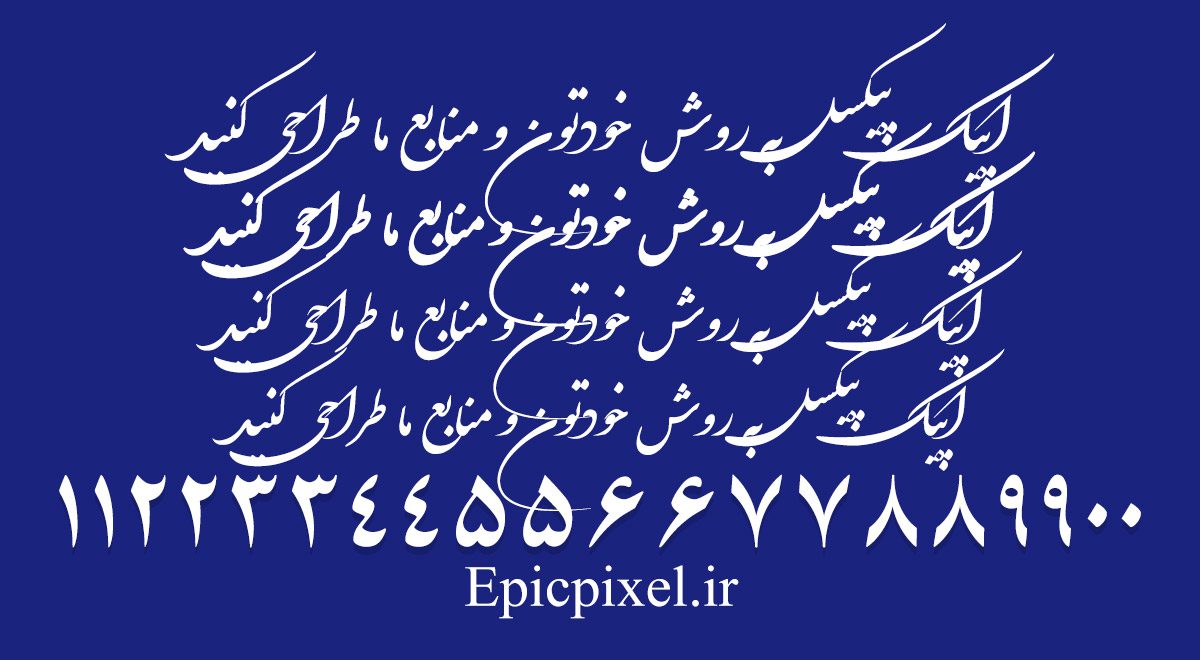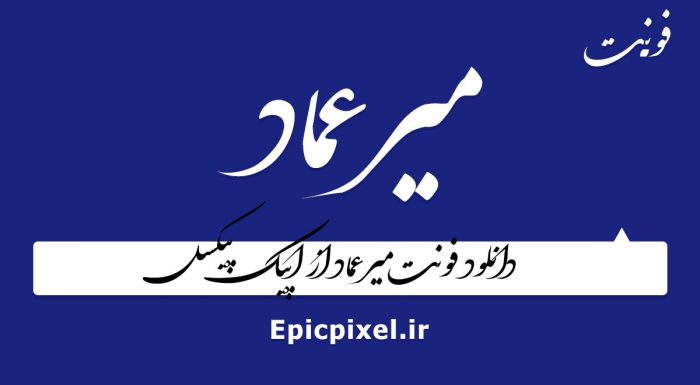
فونت میرعماد فارسی
فونت میرعماد ، ابزار تخصصی خوشنویسی برای طراحانی است که به دنبال احیای هنر خط فارسی در پروژههای دیجیتال هستند. این فونت با پشتیبانی از سبکهای نستعلیق، شکسته، تحریری، ثلث، نسخ، معلی، ریحان و پیرآموز ، تنوعی بینظیر را در دسترس قرار میدهد . طراحی دقیق و ظریف حروف، آن را به گزینهای ایدهآل برای کارت های عروسی، لوگوها، و محتوای چاپی تبدیل کرده است.
میرعماد با دریافت عنوان بهترین ابزار توسعه خط فارسی از وزارت فرهنگ و ارشاد اسلامی، اعتماد طراحان را جلب کرده است . این فونت برای استفاده در پروژههای چندزبانه (فارسی، عربی، لاتین) مناسب است . با فونت میرعماد ، هر طرحی از جزئیات تا عنوانهای بزرگ، حرفه ای و ماندگار خواهد شد.